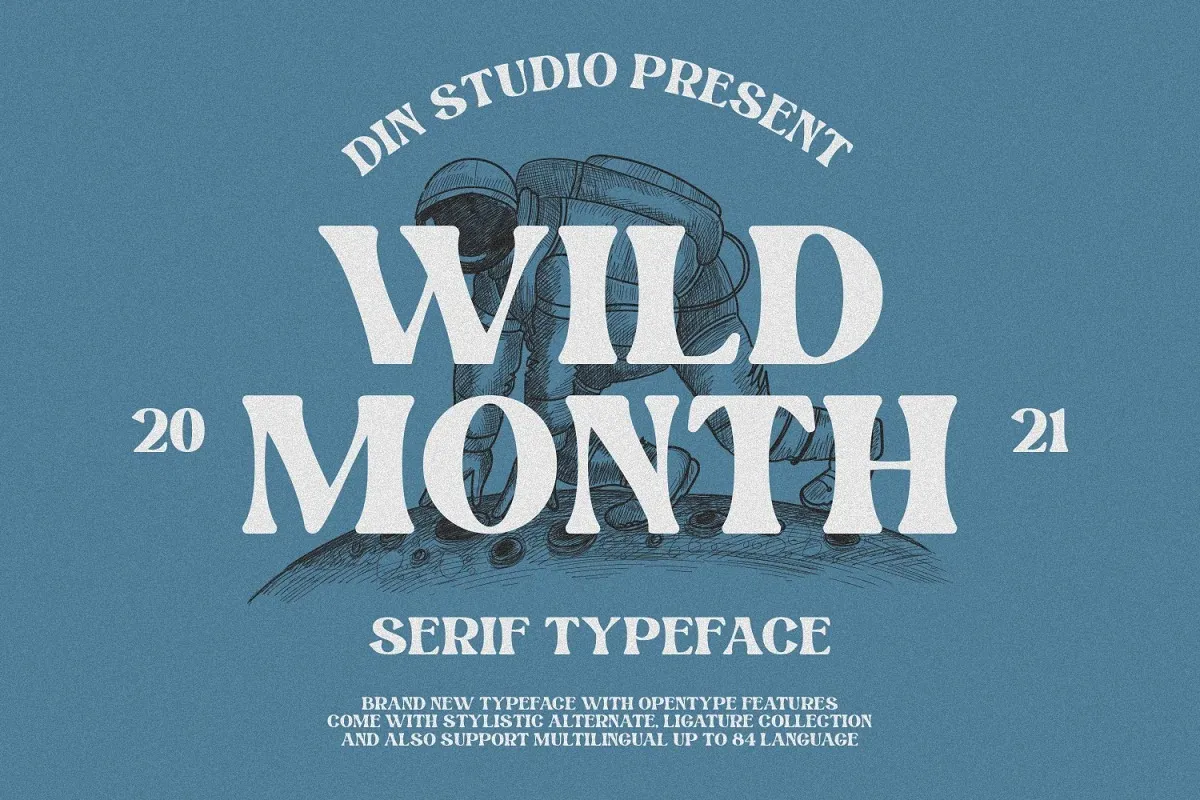
Wild Month Font – Download Grátis
Esta é uma fonte serif simples e elegante que traz diversas funcionalidades de tipo aberto incluindo alternativas estilizadas, formas de inicial e final e ligaturas. Ideal para dar um toque contemporâneo aos seus projetos. Esta tipografia com estilo artístico se destaca por sua interatividade em uma variedade de aplicações e promoções. É a solução perfeita para suas necessidades de logotipo, capa de livro, panfletos, camisetas de marketing, marca e publicidade. Este é um pacote all-in-one completo para ajudá-lo a adicionar profundidade ao seu trabalho.